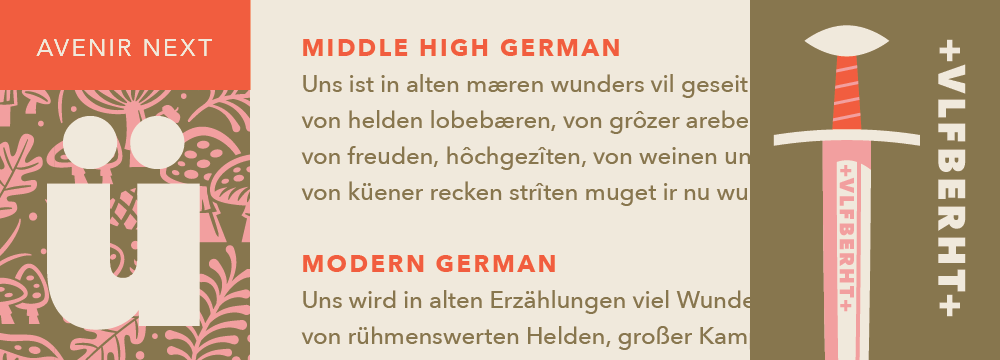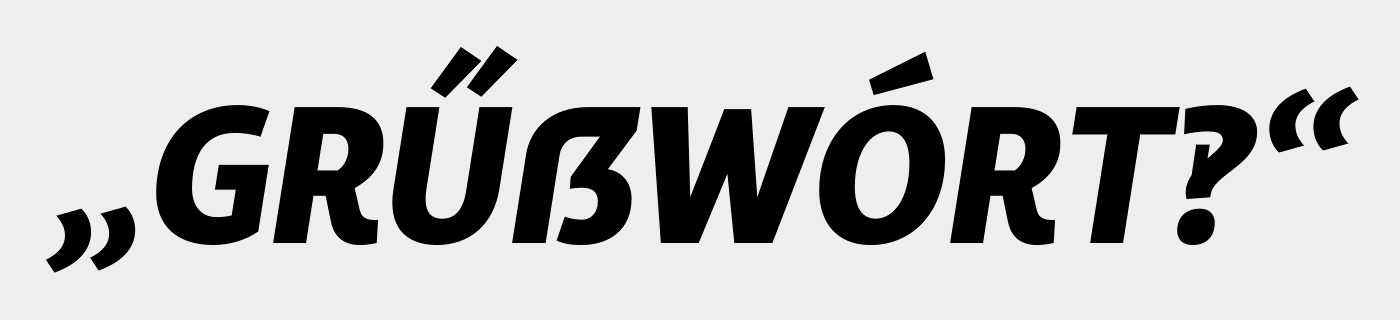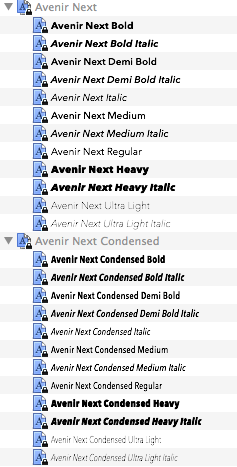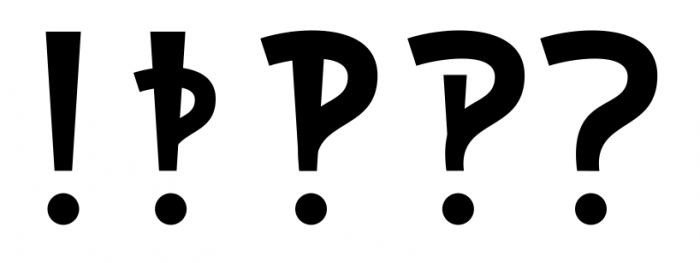
Ja, die E-Mail habe ich heute morgen auch bekommen und gleich die Chance genutzt, mir endlich mal die Bembo zuzulegen. Und die Avenir Next und die Officina Serif … Die Sackers und die Praise gefallen mir auch gut.
Und die Avenir Next
Sieht die bei dir/euch live auch so komisch aus (u und ü ragen ordentlich über andere Minuskeln) wie auf diesem Muster?
Also: Alles fein – die installierten Fonts haben korrekte x-Höhen. Keine Ahnung, warum das Vorschaubild so seltsam aussieht … :-?
Tja, dann habe ich wohl Pech gehabt! Andererseits – ich habe noch OS X 10.9.5 – da ist sie nicht dabei (beziehungsweise nur zwei Schnitte) oder habe ich da etwas komplett übersehen?
Dazu fällt mir ein: Könnte nicht mal ein geschätzter Kollege, der den entsprechenden Überblick* hat, einen FAQ-Eintrag erstellen, in dem man nachschlagen kann, welche Schriften mit welchem OS mitgeliefert wurden?
Heute hat Fonts.com Fontacular unter anderem die ITC Lubalin Graph, die Filson und die Gentona im Angebot. Interessant finde ich alle drei, allerdings scheint mir, dass die Filson nur eine schräggestellte Kursive hat – das finde ich echt schade …
Zuschlagen werde ich vermutlich bei der Compass.  :biglove:
Mit ẞ in Versal- und Kapitälchengröße! :biglove:
Wermutstropfen: Ungarische Doppelakuts passen (wie so oft) nicht; das ‽ ist irgendwie vermurkst. :cry:
Vielleicht haben die ja nur eine noch feinere Abstufung zwischen ? und ! angedacht‽